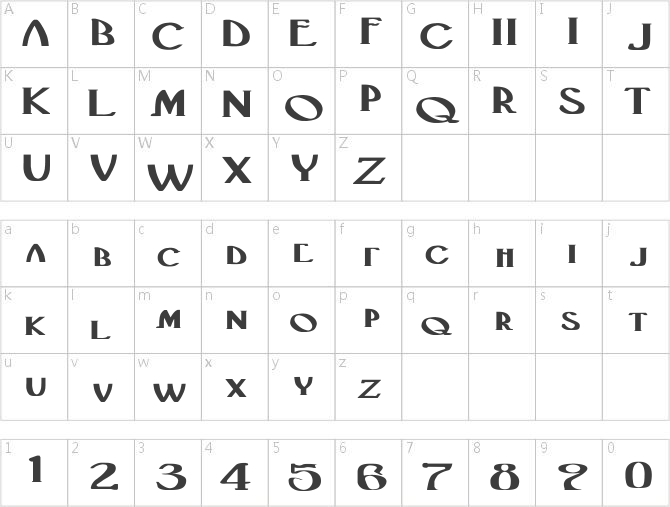
BlackAdderII Extended Bold
BlackAdderII Extended Bold介绍
BlackAdderII Extended Bold字体字库是一款让人赏心悦目、百看不厌的英文字体,适合各类广告和产品包装设计应用,字体大小0.09MB,格式为ttf字体,上传用户是小李哥/,作者/版权方为未知